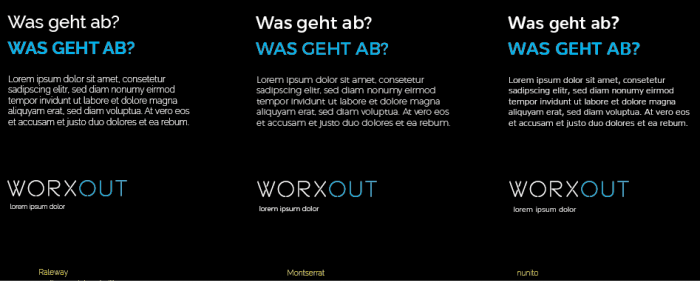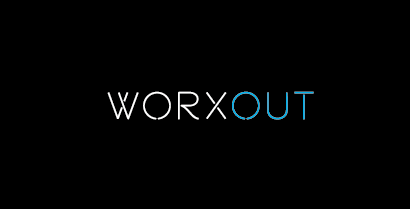
Runde Font zu rundem Logo
ich wende mich an euch in der Hoffnung, dass ihr mir vl ein paar Tips geben könnt.
Schriften sind allgmein nicht so Meines - schon gar nicht Kombinationen.
Ich suche für das Logo im Anhang eine schöne und wenn möglich kostenlose Hausschrift, welche ich
überall verwenden kann. (Beim Claim, Überschriften, Fliesstext usw.)
Da die Buchstaben des Logo ja recht breit sind, kommt ja meiner Meinung nach nur eine breite Schrift in Frage oder?
Persönlich gefällt mir zB die Ubuntu, welche aber stilistisch so gar nicht zum Logo passt - von der Breite her aber optimal.
Die Frage ist allgemein ob ich eine ähnlich runde Schrift verwenden soll oder durch eine eckige einen Kontrast reinbringen soll?
Als runde Variante hätte ich jetzt mal die Comfortaa versucht, womit aber alles wieder zu verspielt aussieht.
Bisher hatte ich immer die Arial als Hausschrift benutzt, welche ich aber einfach gerne wechseln würde, weil diese ja doch überall verwendet wird. Den Fliesstext hatte ich immer in regular und die Überschriften in Blockbuchstaben (was ich wahrscheinlich auch beibehalten würde) um ein bisschen mehr Spannung reinzubringen. Den Kontrast mit den eckigen Buchstaben hab ich eigentlich auch gut gefunden persönlich und laienhaft.
Source Sans Pro, Ubuntu und Ähnliche finde ich halt super, weil es so viele Schnitte gibt - nach ewig langem probieren komme ich aber immer wieder drauf, dass ich eigentlich gar nicht weiss was am besten passt. Ich möchte einfach nur dass die Texte und Überschriften leicht lesbar sind und auch zum Logo passen. Es muss jetzt nicht besonders futuristisch sein wie die Ubuntu, aber charakteristisch zum Logo passen wäre schon gut.
Ich denke da funktioniert viel und es kommt wie immer auch etwas auf den Kontext, etc. an.
Wenn es eher harmonieren soll und Du einen Rounded-Font ergänzen möchest, würde ich mir die Bryant oder Gotham rounded ansehen.
Ich denke aber, es muss nicht mal unbedingt rounded sein, auch Fonts wie die Cera dürften gut dazu passen.
Schöne geometrische, rounded Freefonts mit vielen Schnitten (inklusive Kursive) fallen mir keine ein – geometrische, die halbwegs lesbar und ästhetisch sind, wären aus meiner Sicht die Montserrat oder die Raleway (wieder mit gekreuztem w).
Die Comfortaa mag formal ganz gut passen, aber als Brotschrift halte ich sie für ungeeignet. Wenn es rounded und free sein soll, dann wirf mal einen Blick auf die Nunito.
vielen vielen Dank für deine total wertvollen Tips! Ich hab jetzt mal die Raleway, Montserrat und die Nunito probiert - also alles was ich jetzt testweise runterladen konnte. Ja die Corporative Sans wäre natürlich ein guter Deal - aber ich nach dem Herumprobieren finde ich fast eine eckige besser - siehe Anhang. Oder vl sollte ich auch Schriften mischen für die Überschriften zB?
Momentan tendiere ich sehr zur Raleway. Das W ähnelt sich wirklich sehr, obwohl es ein bisschen breiter ist als beim Logo.
Anbei findest du mal meinen Skizzenzettel.